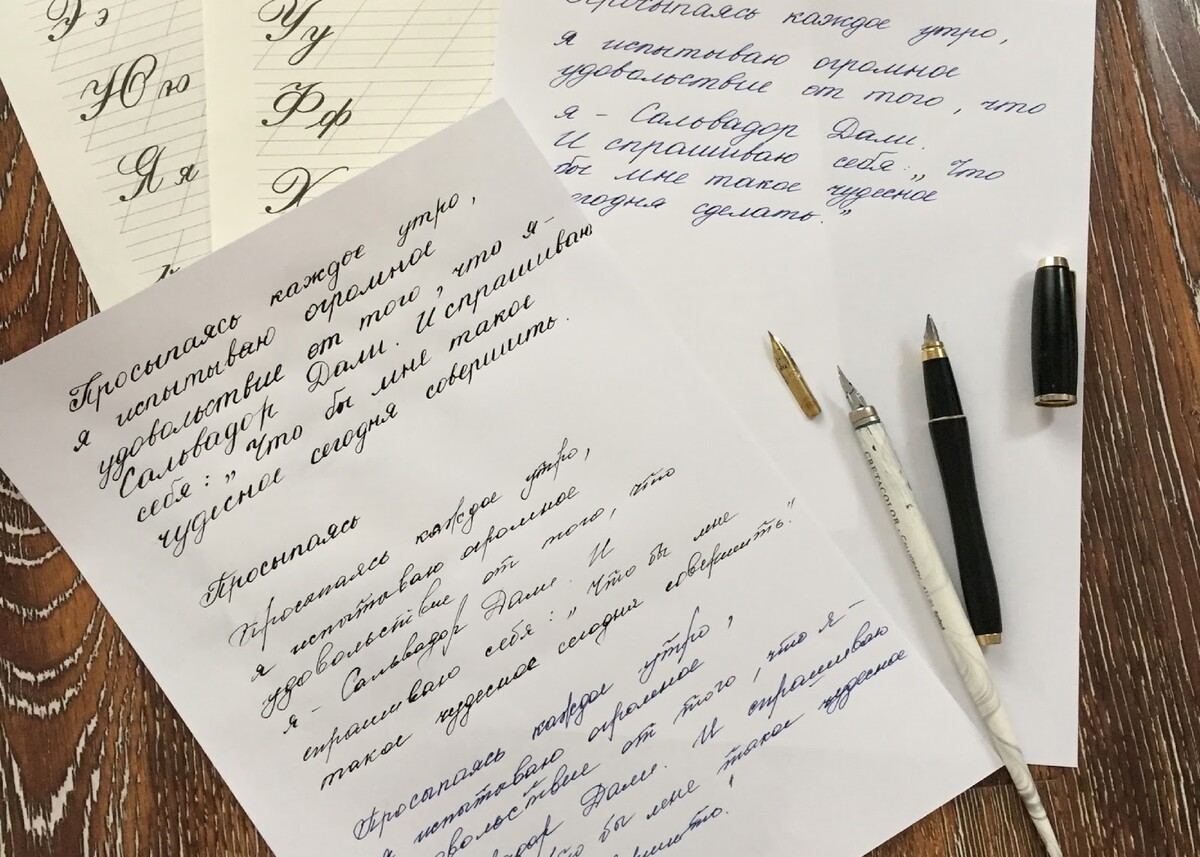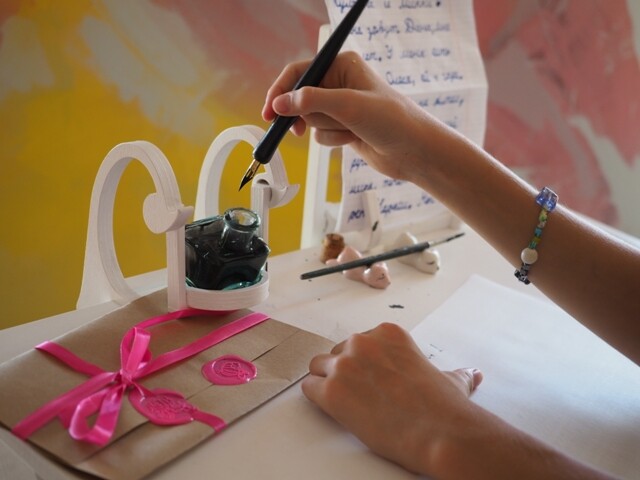
За всю жизнь я встречала только одного человека с идеальным красивым почерком. Что бы он ни писал, в любой ситуации, это смотрелось очень эстетично. В моих детских глазах это было идеалом письма.
И этот человек был мой ПАПА
В наших семейных архивах хранилась его тетрадь - ученика первого класса. Идеальное исполнение всех букв, без ошибок, без помарок, одни пятерки. Вся, вся тетрадь от корки до корки.
Как это вообще возможно?!!! В первом классе!!!
Я любила ее рассматривать и мечтать о таком же красивом почерке.
А еще у нас были фотоальбомы парашютистов (моих родителей), наши детские истории, архивные стенгазеты и плакаты. Все это оформлялось папой очень стильно, разными шрифтами и иллюстрациями.
Вообщем, он умел красиво писать и использовал это умение для разных оформительских и просто жизненных целей.
А еще он всегда писал чернильной ручкой и для меня это была еще одна мечта!!!
И вот я пошла в школу. И что подарил мне мой папа?
Конечно! Чудесную чернильную ручку с тонким закрытым пером и банку чернил.
Папа для меня был волшебником. Совершенно неосознанно он создал атмосферу магии вокруг письма и инструментов, связанных с ним.
Как у него это получилось? Ответ прост - папа сформировал позитивную доминанту.
Вот как это работает.
Когда вы занимаетесь каллиграфией самостоятельно, с интересом и увлеченностью погружаясь в письмо, ребенок впитывает ваши ощущения, ваше удовольствие от дела. С этого момента для него образы букв и то, что вы пишете рукой, заходит на подкорку как часть процесса, который мама любит, как приятная часть жизни. Именно так формируется позитивная доминанта.
В детском сознании фиксируется “вот нам с мамой хорошо. А что мы делали? Буквы рисовали”. На эту тему прикрепляется очень много хороших, благостных чувств и воспоминаний. Они накапливаются и в момент, когда своевременность для письма наступает, у ребенка уже будет это позитивное внутреннее состояние. Оно начнет транслировать в мозг удовольствие и ему, естественно, захочется заниматься письмом вновь и вновь.
Я уверена, что любой процесс можно внедрить в свою практику позитивным способом. Важно посмотреть на особенности ребенка, есть ли у него к этому желание и склонность.
Это нужно делать, потому что при принятии решения нами руководит мозг. Он не всегда делает выбор в пользу того, что для нас действительно ценно и полезно. Он делает выбор на основании того, что на его взгляд, принесет нам наибольшее удовольствие. Попросту - мозг стремится испытать счастье.
Мы же можем повлиять на это тем, что будем осознанно формировать счастливые моменты. Основа этого - совместный процесс вместе с мамой, когда все легко, свободно, спокойно, в эксперименте, когда пусть не все получается, но мы вместе и можем в этом развиваться, если захотим.
Нет строгих возрастных рамок. Когда ребенок рождается, вы сразу становитесь носителем позитивной доминанты, но будете вы ее использовать или нет, зависит от вас.
Всю начальную школу я была странной девочкой с чернильницей.
Сказать, что на меня смотрели странно, значит ничего не сказать…
Все писали шариковыми ручками. А передо мной на столе стояла чернильница и каждый раз, когда резервуар ручки пустел, я набирала чернила и продолжала письмо.
Еще у меня были специальные промокашки в тетрадях (если кто-то еще помнит что это такое). Руки измазаны в чернилах, но я была довольна.
Не обходилось и без приключений.
Мальчик Сережа, видимо из честной симпатии ко мне, частенько выливал мне чернила на белый фартук. Я плакала. А папа приходил защищать меня! И покупал мне новую банку.
И так, всю начальную школу я была странной девочкой с чернильницей.
Со временем все это забылось надолго.
Вчера я попросила папу написать пару строк обычным своим почерком и почерком 1 класса =)
Вот, что получилось. Вот они мои любимые)) и такие особенные, папой созданные, выносные элементы буквы "Р" и "Ж" и птички над буквой "Т"
“Просыпаясь каждое утро, Я испытываю огромное удовольствие
от того, что Я - Сальвадор Дали.
И спрашиваю себя: "Чтобы мне такое чудесное сегодня совершить?"
Много лет спустя мой средний брат, сейчас известный дизайнер и граффити художник Andrey Adno, а тогда юный выпускник школы, поехал поступать в художественное училище.
И после каждого курса, возвращаясь летом домой, он привозил коллекцию своих работ по разным дисциплинам. Из всего многообразия живописи, карандашного рисунка, графики и прочих направлений меня больше всего привлекали ШРИФТЫ.
Этот предмет шел отдельным курсом, где они вручную вырисовывали буквы очень точно, очень аккуратно. И не дай бог на пол миллиметра будет штрих длиннее (или короче) вся работа перечеркивается ииииии.... недели труда фффтопку.
Увидев мое увлечение каллиграфией, Андрей отыскал свои старые работы и рассказал про технику "отмывки" в монохромном изображении. Это очень долгий процесс создания вручную градиента на буквах, многократные наслоения тона, где каждый миллиметр имеет значение.
И теперь это Игра в каллиграфию.